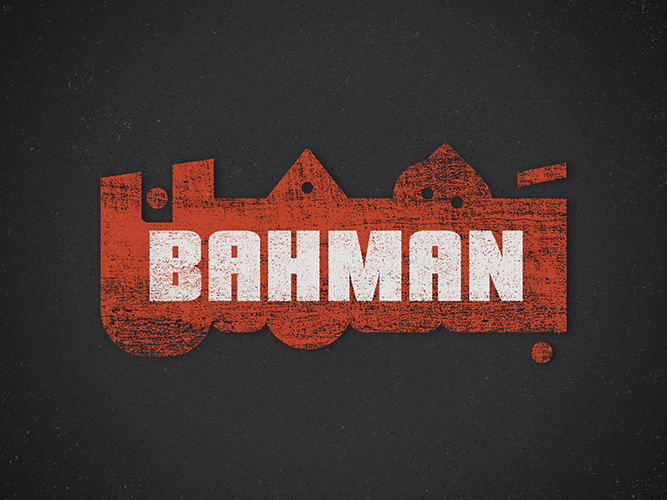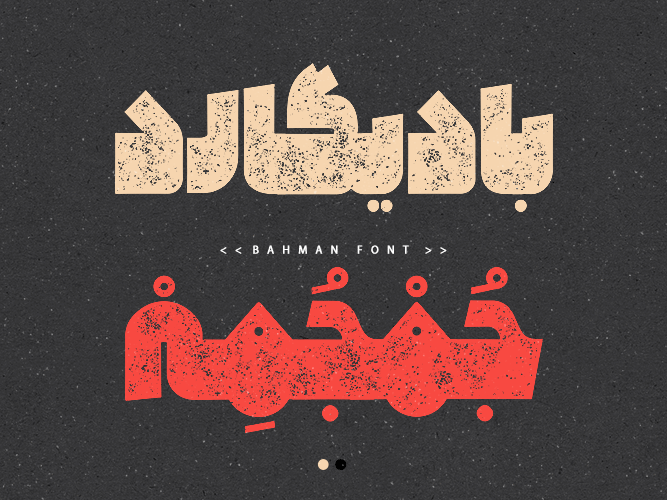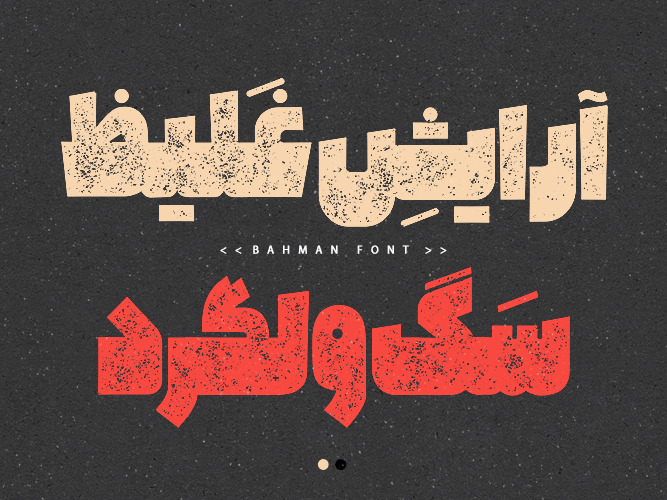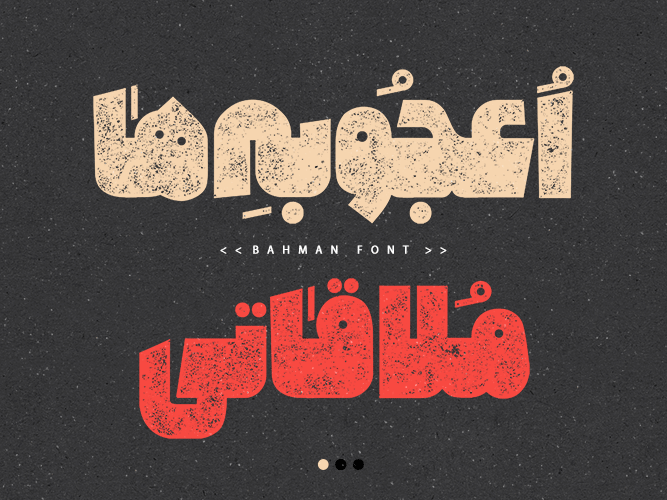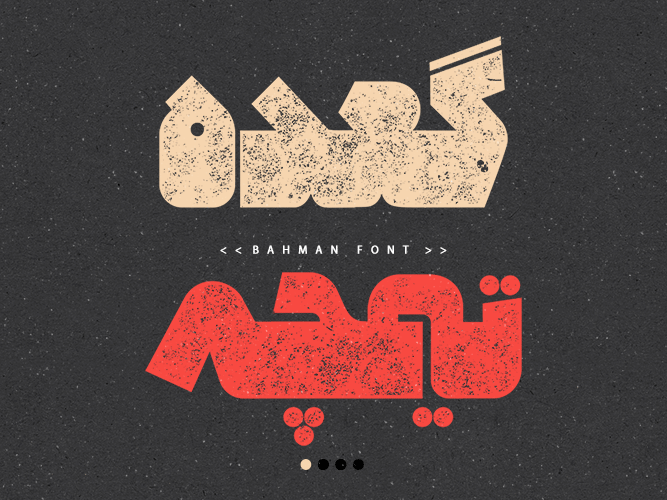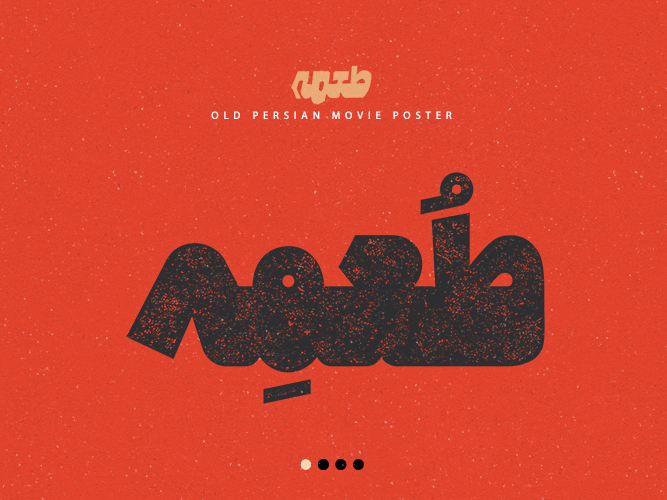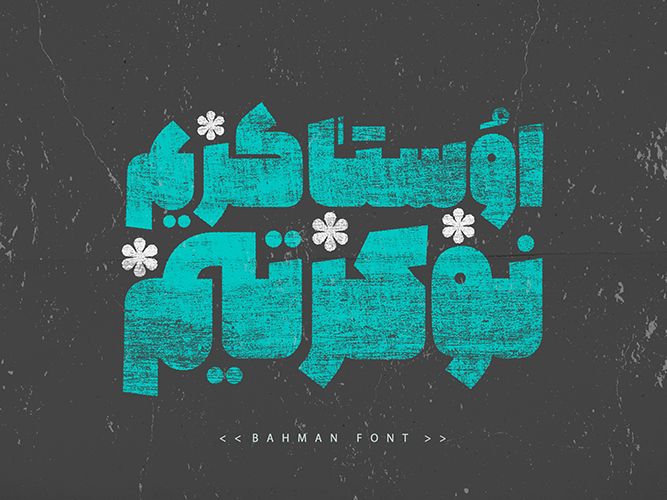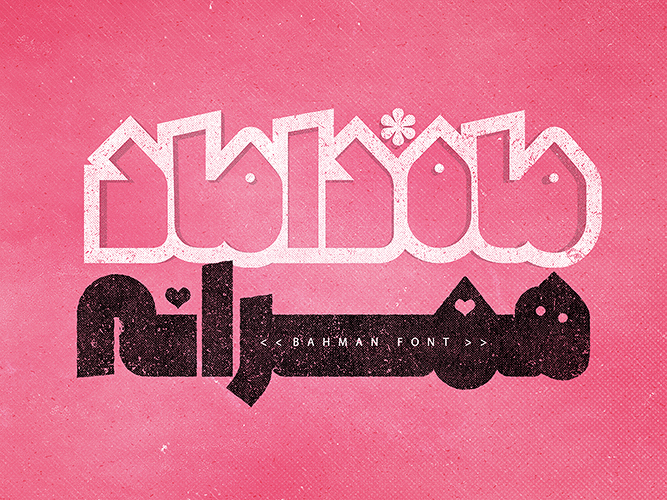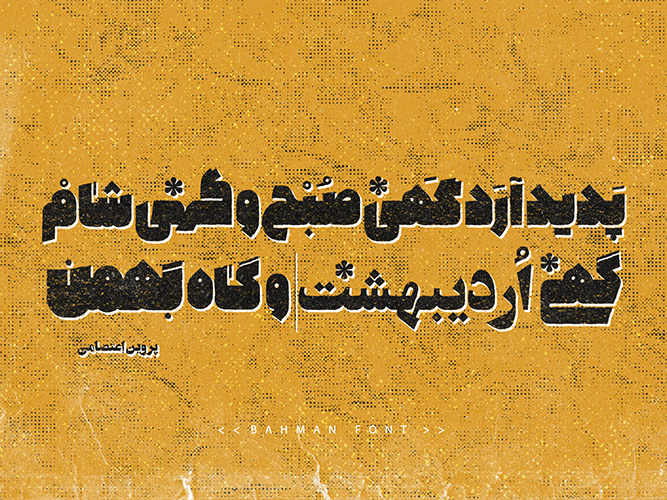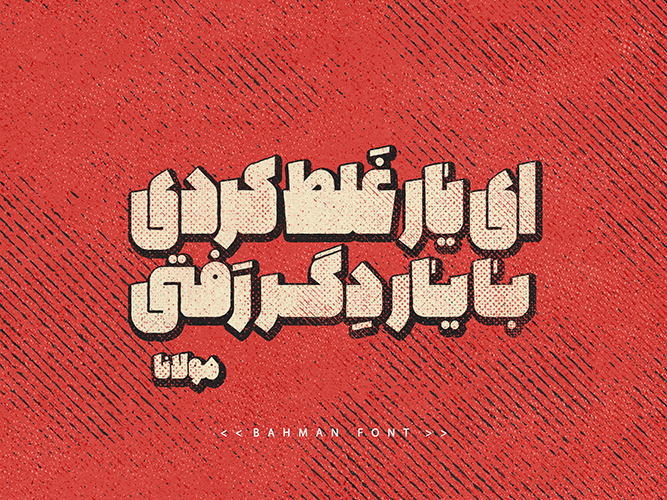
درباره قلم بهمن
قلم «بهمن» با اقتباسی آزاد از پوسترهای سینمایی قبل و بعد از انقلاب و با حال و هوای مدرن و با نگاهی به فونتهای سنگین عربی، در اردیبهشت ماه ۹۳ توسط «احسان و علی جعفر پیشه (صریر)» به عنوان یکی از اولین تجربههای ساخت تایپ فیس و قلم فارسی شخصی، کلید خورد و در بهمن ماه ۹۶ به همت گروه نرم افزاری مریم به اتمام رسید و در قالب فونت، به صورت عمومی منتشر میشود.
این فونت صرفا بازسازی تایپهای پوسترهای سینمایی قدیمی نیست و با تجربه و اتود زدنهای فراوان طراحان آن به ثمر نشسته است. در این دست تایپها که اغلب برای تیتر در سینما و روزنامه کاربرد داشته، سعی شده که از تکلفهای بیمورد در فرم و اجرا دوری شود و با وزن خیلی سنگین خود در صدد جذب مخاطب و انتقال پیام باشد. این فونت قابل استفاده درفضای پوستر، طراحی لوگو، طراحی عنوان و تیتر نشریه، کتاب کودک، تابلوسازی و ... با کاراکتر محدود میباشد.
ساخت این قلم بر اساس یک نوستالژی شکل گرفته و ماهیت سینمایی دارد و از آنجا که تیم طراح از اردیبهشت ماه ۹۳ طی یک هدفگذاری ۵ ساله به تولید ۱۲ فونت ( که ۷۰-۸۰ درصد این مسیر طی شده) همت گمارده و نام گذاری اغلب آنها به نام ماه های سال را، در دستور کار خود دارند (شایان ذکر است که حسن مطلع این حرکت با قلم اردیبهشت آغاز و با قلمهای مهر، بهمن و به زودی اسفند، فروردین، و خرداد ... ادامه پیدا خواهد کرد)؛ لذا طراحان آن، قلم مذکور را در بهمن ماه ۹۶ (که سینماییترین ماه سال به شمار میرود) به اتمام رساندند و نام «بهمن» را به آن اختصاص دادند.
از ارزش افزودههای ویژه این قلم، علاوه بر نوستالژیک بودن و وزن بسیار سنگین آن، میتوان به تعدد و تنوع وسیع لیگچرها (جفت حروف خاص) و مخصوصا آلترناتیوها (حروف جایگزین) در حروف، نقاط و حتی اعراب اشاره کرد که قابلیت ویژهای را برای گرافیست در زمینه تایپوگرافی ایجاد میکند تا بر اساس سلیقه خود بهترین فرمی که مد نظر هست را انتخاب و به کار بگیرد (و با توجه به قابلیت فرمی حروف، اقدام به تایپوگرافی های شخصی و دخل و تصرف در زوایا و ارتفاع حروف و... نماید). در واقع میتوان گفت فونت بهمن ، چند فونت در یک فونت هست و این حجم تعریف آلترناتیو برای یک فونت فارسی بیسابقه است.
پیشنهاد میشود حتما در حین کار با فونت، حالت لیگچر در نرم افزار را خاموش و روشن کنید و با انتخاب حروف و نقاط و ... و زدن کلیدهای ترکیبی Alt+H بعد از آنها، از حالت های مختلف آلترناتیو تعبیه شده در فونت بهترین استفادهها را ببرید.